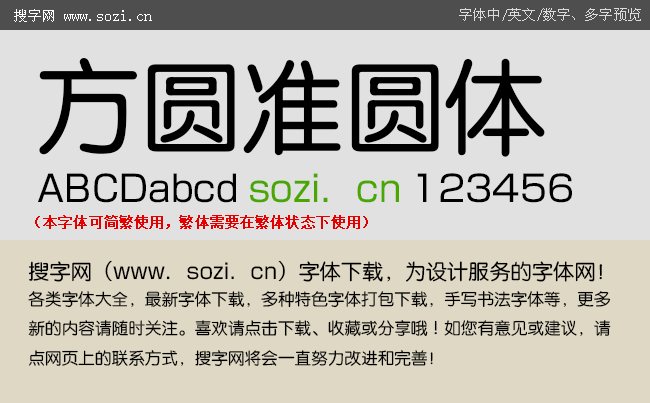
方圓準(zhǔn)圓體
搜字網(wǎng)提供方圓準(zhǔn)圓體中文藝術(shù)字體下載,方圓準(zhǔn)圓體是一款應(yīng)用于設(shè)計方面的中文簡體漢字,該字體字體大方圓潤,又十分工整大氣,整體效果十分出色,可以應(yīng)用于廣告設(shè)計、名片設(shè)計、包裝印刷、產(chǎn)品設(shè)計等應(yīng)用。